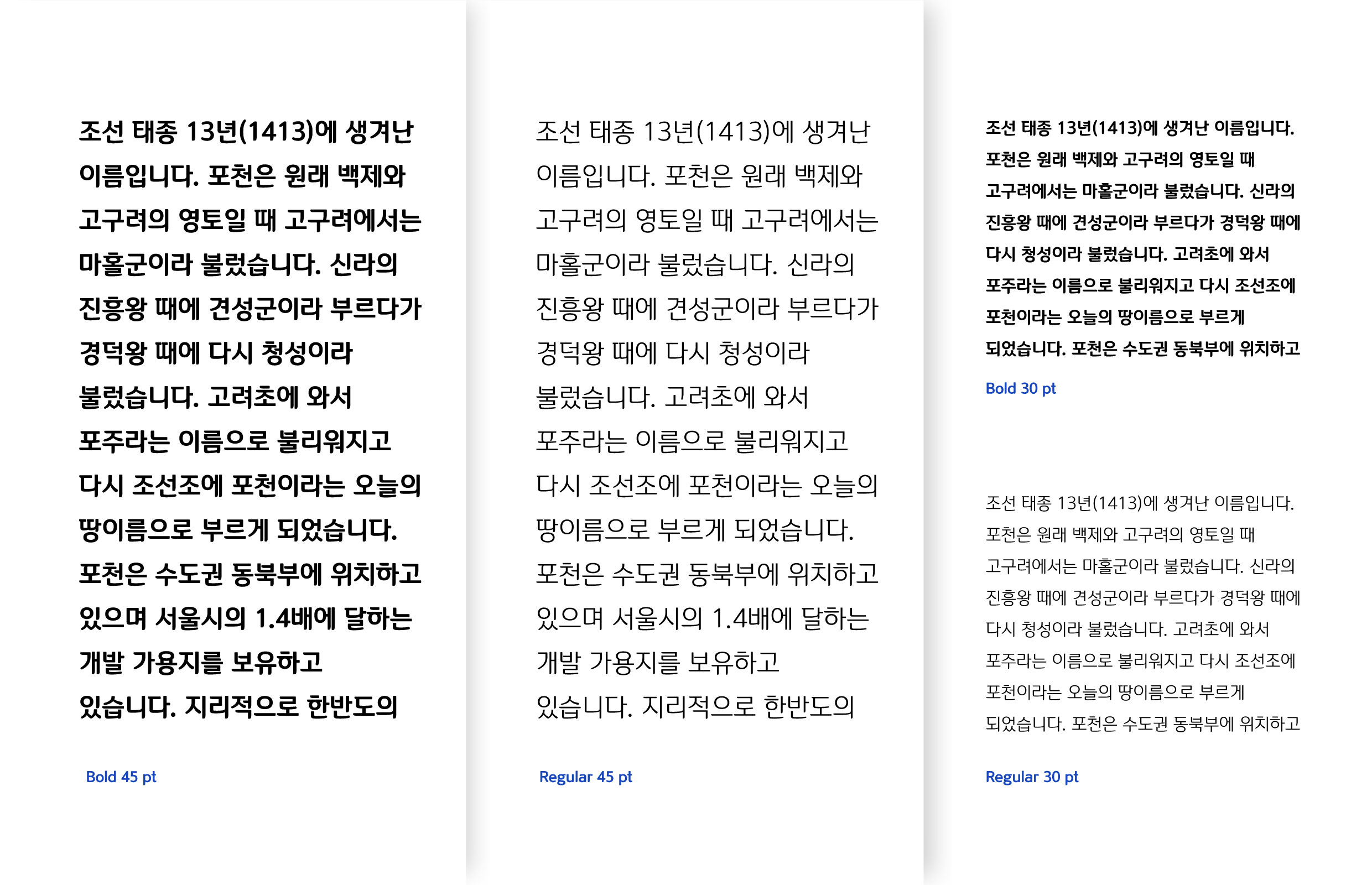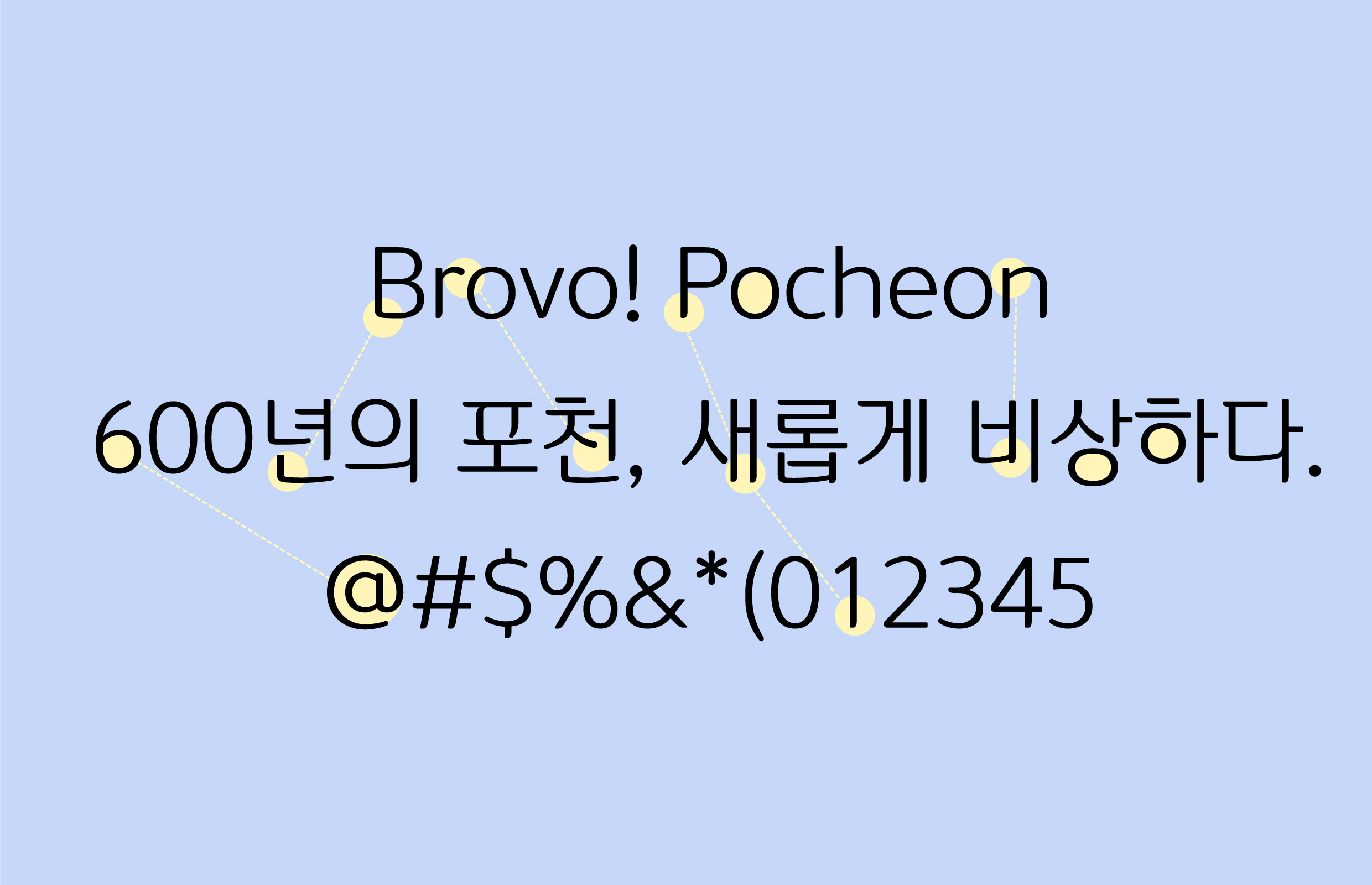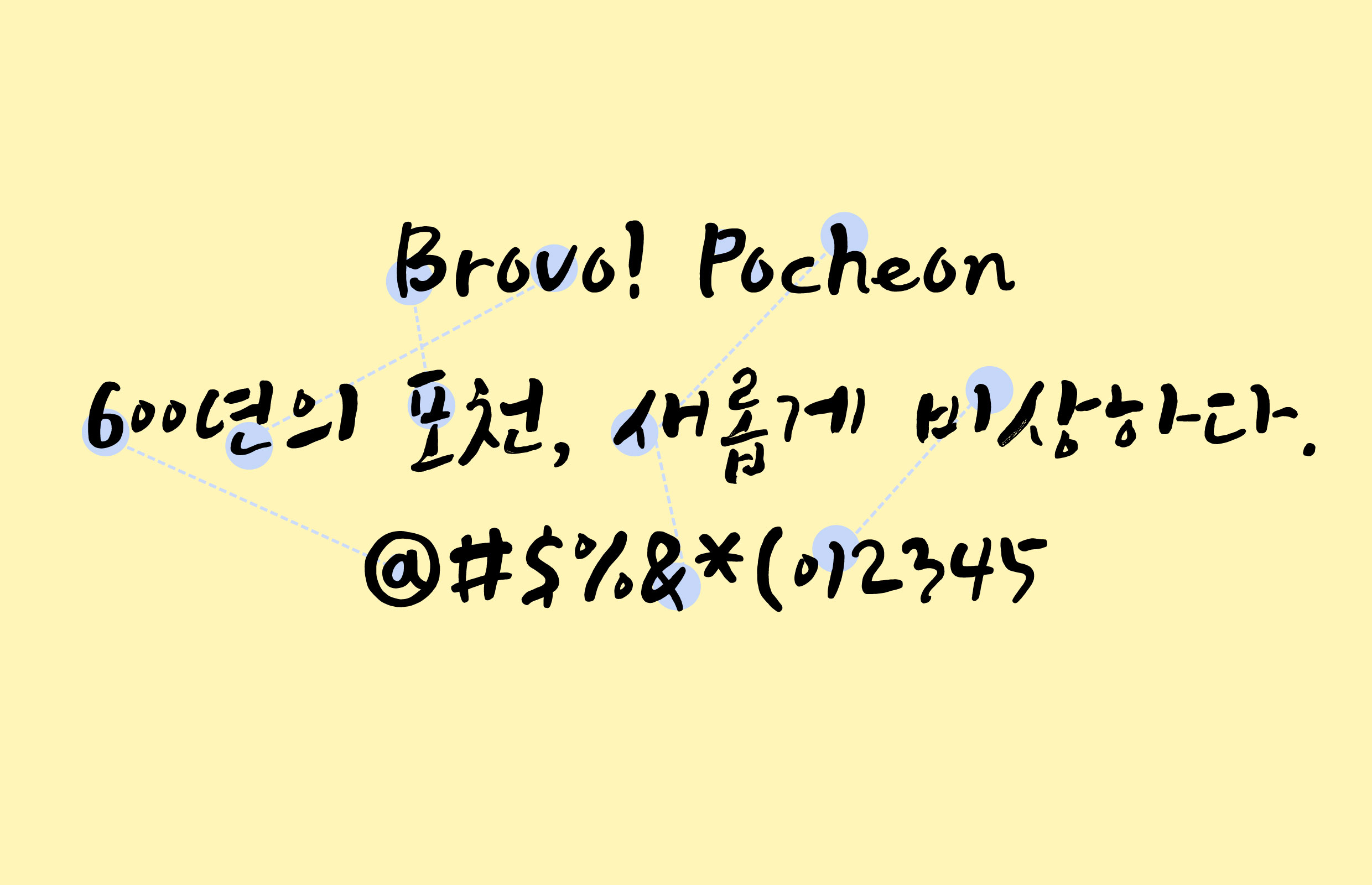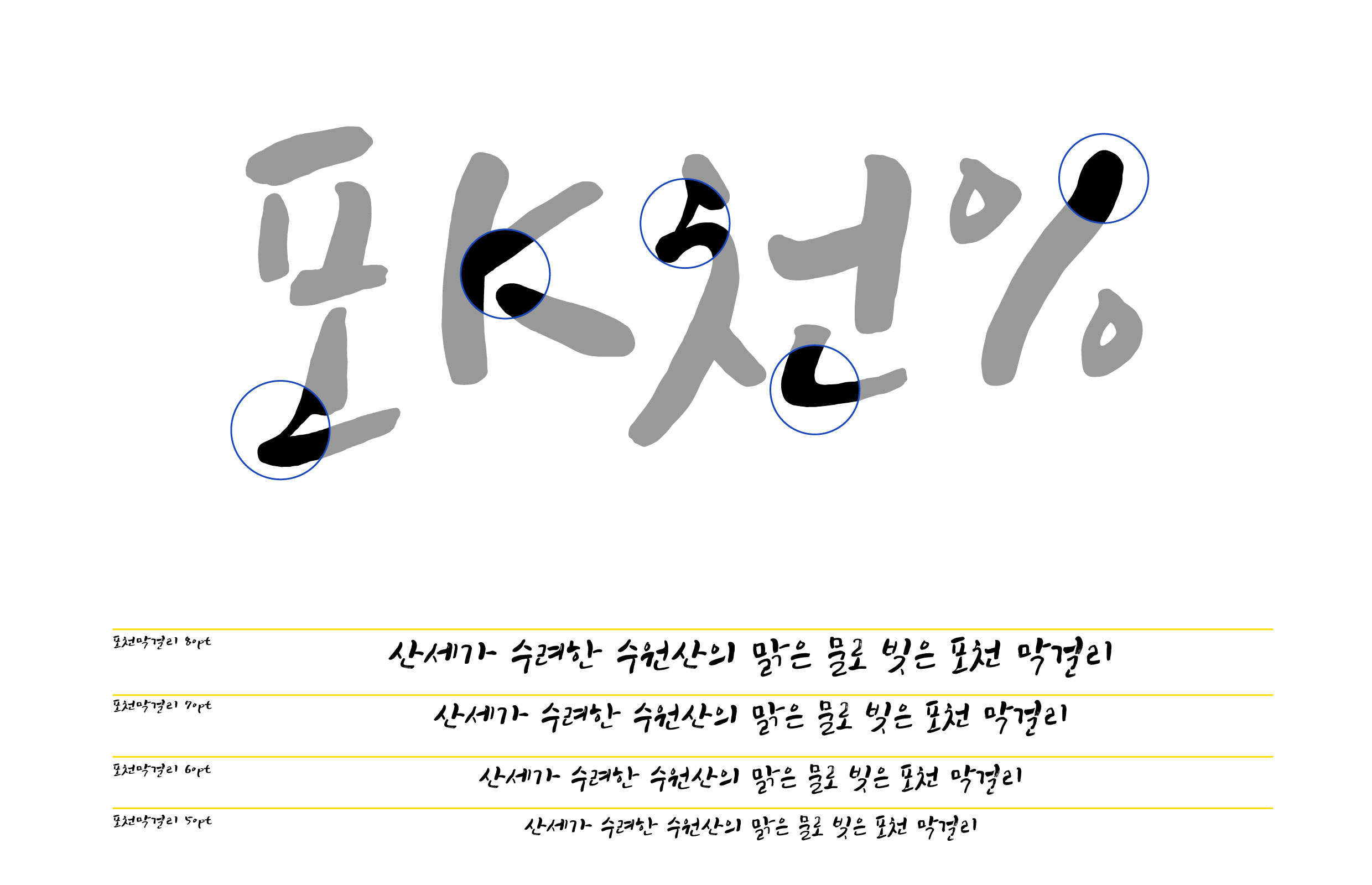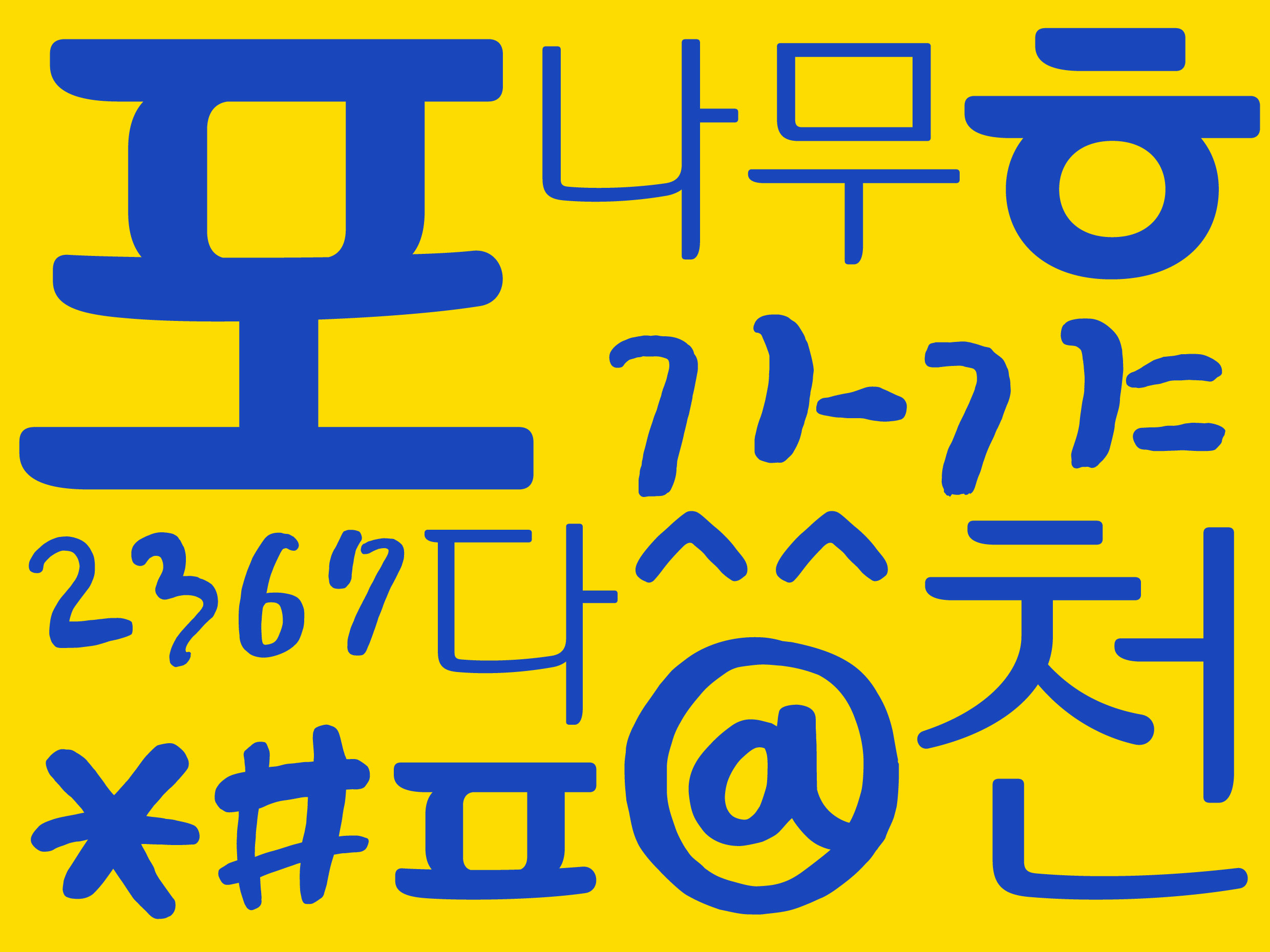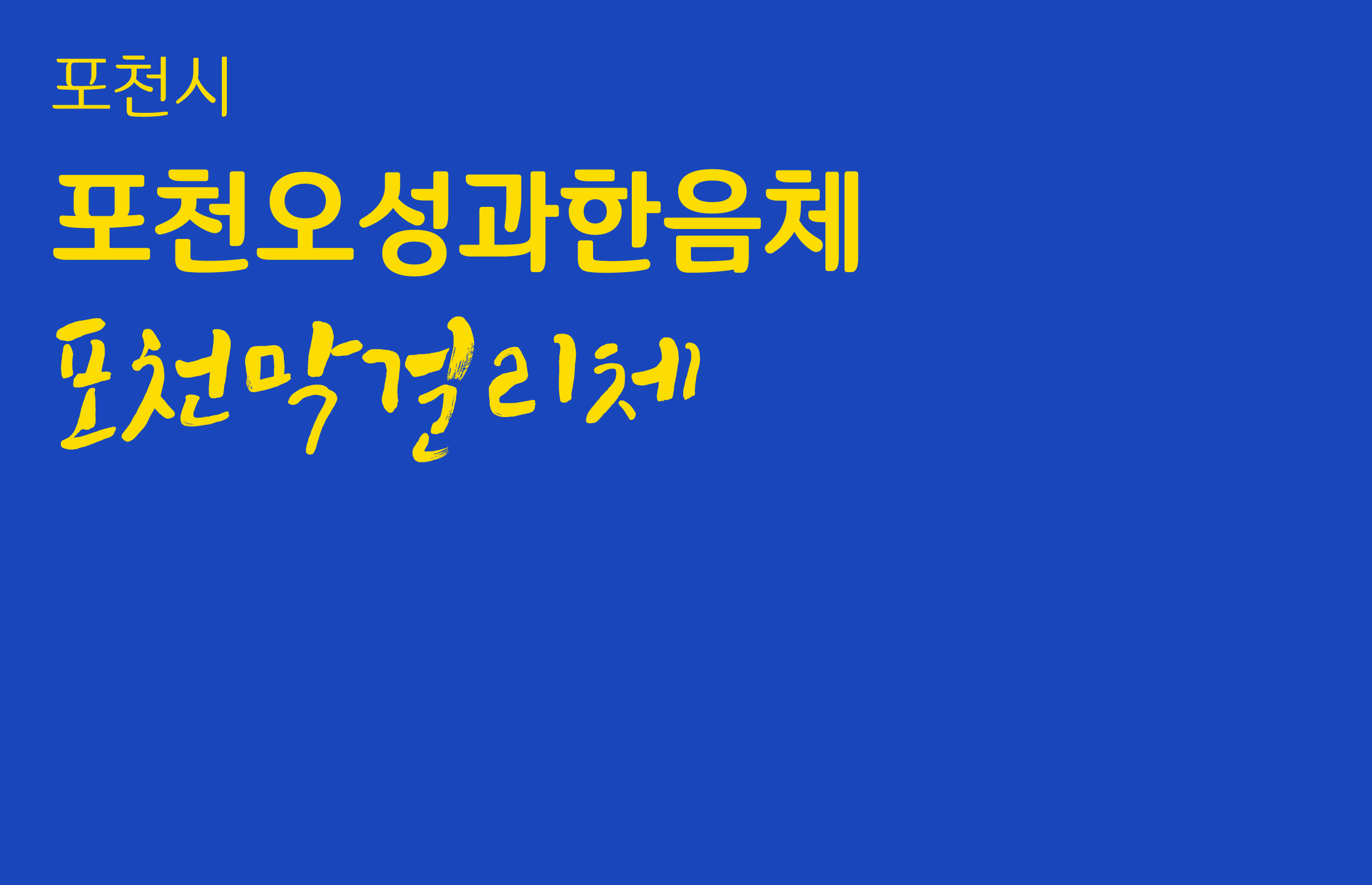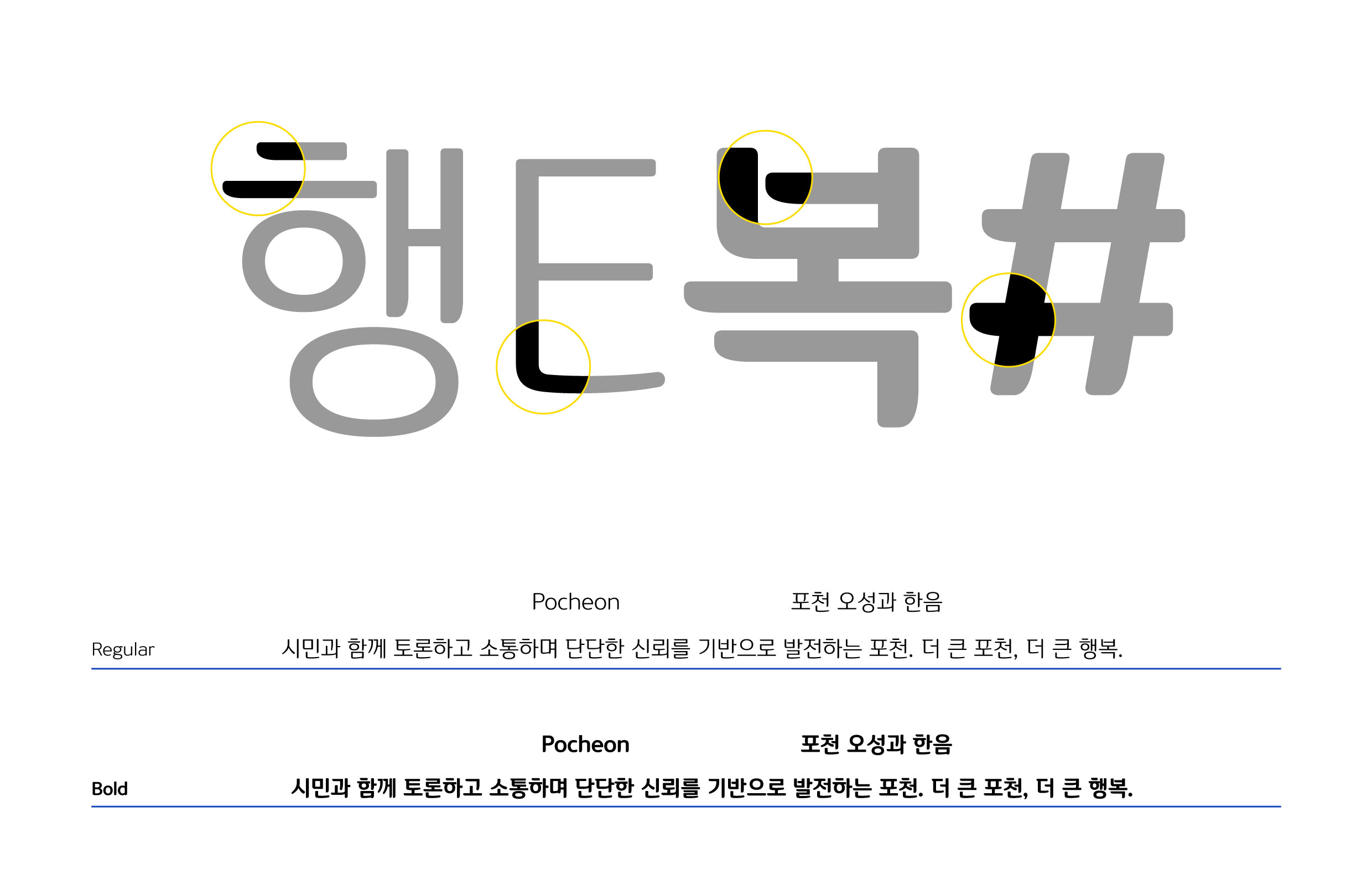
포천시
포천시 [포천오성과한음체, 포천막걸리체]
‘포천 오성과 한음체’는 판본체의 특징을 적용하여 전체적으로 고딕의 형태를 가지고 있으며, 끝맺음의 굵기 변화와 획의 부드러운 곡선 형태에서 명조의 특징 또한 엿볼 수 있다. ‘포천 막걸리체’는 포천을 대표하는 음식 막걸리를 형상화하여 제작했으며, 강약의 필력감이 돋보이는 캘리스타일의 제목용 서체다.